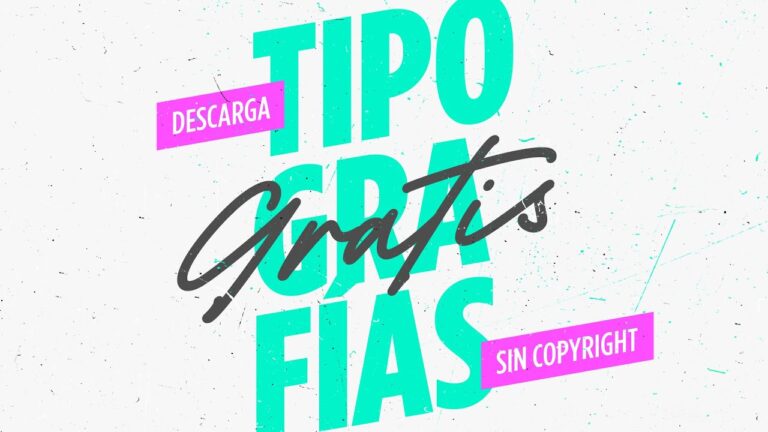
Fuentes Innovadoras: Revolucionando la Tipografía
En un mundo donde la comunicación visual se vuelve cada vez más relevante, las fuentes innovadoras en tipografía emergen como protagonistas en el diseño gráfico contemporáneo. Estas tipografías no solo desafían las convenciones estéticas, sino que también aportan un aire fresco y original a la identidad visual de marcas y proyectos creativos. A medida que los diseñadores buscan maneras de capturar la atención del público, las fuentes innovadoras se convierten en herramientas clave para transmitir mensajes de forma operativa y memorable. Exploraremos cómo estas tipografías están revolucionando la forma en que percibimos y nos conectamos con el contenido visual.
Ventajas
• Estética única: Las fuentes innovadoras en tipografía ofrecen un diseño distintivo que puede atraer la atención y destacar un proyecto o marca frente a la competencia.
• Versatilidad en aplicaciones: Estas fuentes pueden adaptarse a diversas plataformas y formatos, desde medios impresos hasta digitales, lo que permite una comunicación operativa en diferentes contextos.
• Reflejo de modernidad: El uso de tipografías innovadoras puede asociar una marca o proyecto con tendencias contemporáneas, transmitiendo una imagen de frescura y creatividad.
Desventajas
• Limitaciones de legibilidad: Muchas fuentes innovadoras en tipografía pueden sacrificar la legibilidad en favor de la creatividad, lo que dificulta la lectura de textos largos o en tamaños pequeños.
• Dificultad en la compatibilidad: Algunas fuentes innovadoras pueden no ser compatibles con todos los dispositivos o programas de diseño, lo que puede generar problemas en la presentación y visualización de contenidos.
• Sobrecarga visual: El uso excesivo de fuentes innovadoras puede resultar en una sobrecarga visual para el espectador, haciendo que el mensaje principal se pierda entre los elementos de diseño.
• Tendencias efímeras: Las fuentes innovadoras a habitual están sujetas a modas pasajeras, lo que puede llevar a que un diseño se vuelva obsoleto rápidamente y requiera actualizaciones frecuentes para mantenerse relevante.
¿Qué se entiende por fuentes modernas?
Las fuentes modernas se caracterizan por su diseño basado en líneas y formas geométricas, lo que les confiere una apariencia limpia y clara. Este estilo no solo facilita la lectura, sino que también permite que el mensaje se comunique de manera operativa, sin distracciones innecesarias. Su simplicidad es un rasgo distintivo que las convierte en una elección popular en el mundo del diseño gráfico.
Además de su legibilidad, las fuentes modernas pueden incorporar detalles creativos que añaden un toque de frescura y contemporaneidad a cualquier proyecto. Estas tipografías son ideales para transmitir una imagen profesional y actual, lo que las hace perfectas para marcas que buscan destacar en un mercado competitivo. Con la elección adecuada, pueden transformar la percepción de un diseño.
Si estás buscando darle un impulso moderno a tu trabajo, explorar una colección de 50 tipografías puede ser la clave. Cada fuente ofrece una variedad de estilos y matices que pueden adaptarse a diferentes necesidades y personalidades de marca. La incorporación de estas fuentes en tus diseños no solo mejorará su estética, sino que también resonará con una audiencia que aprecia la modernidad y la innovación.
¿Cuál es la tipografía más elegante?
La fuente Helvética se destaca por su diseño limpio y contemporáneo, siendo una de las tipografías más reconocidas en el mundo del diseño gráfico. Su aspecto minimalista y su legibilidad la convierten en una opción preferida para diversas aplicaciones, desde logotipos hasta publicaciones editoriales. Esta fuente refleja una estética sofisticada que atrae tanto a profesionales como a aficionados del diseño.
Además de su elegancia, Helvetica comunica un sentido de confianza y claridad, lo que la hace ideal para marcas que buscan proyectar una imagen moderna y profesional. Su versatilidad permite que se adapte a diferentes estilos y plataformas, manteniendo siempre un aire de distinción. Sin duda, Helvética es la elección perfecta para quienes desean elevar la presentación visual de sus proyectos.
¿Cuál será la tendencia en fuentes para 2024?
En 2024, una de las fuentes más destacadas en el diseño gráfico es la tipografía sans serif. Este estilo minimalista se ha convertido en un favorito entre diseñadores por su claridad y versatilidad, adaptándose tanto a soportes digitales como impresos. La tendencia se aleja de las fuentes más ornamentadas, priorizando la legibilidad y la simplicidad, lo que permite que el contenido se comunique de manera operativa y directa.
Otra tendencia notable es la incorporación de fuentes personalizadas. Cada vez más marcas buscan destacar su identidad única a través de tipografías diseñadas específicamente para ellas. Esto no solo les da un carácter distintivo, sino que también refuerza su mensaje y conexión emocional con el público. Las fuentes personalizadas están siendo utilizadas en logotipos, sitios web y campañas publicitarias, marcando una diferencia en un mercado saturado.